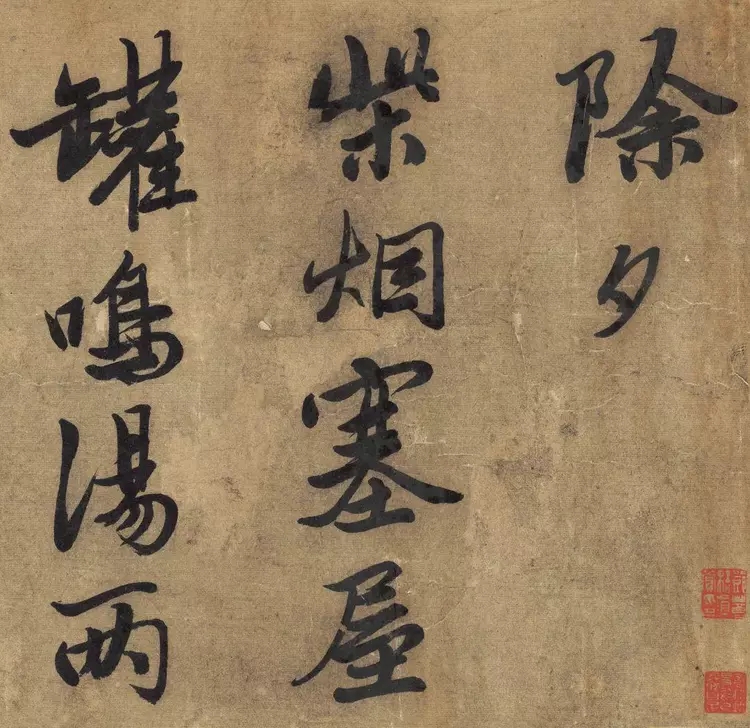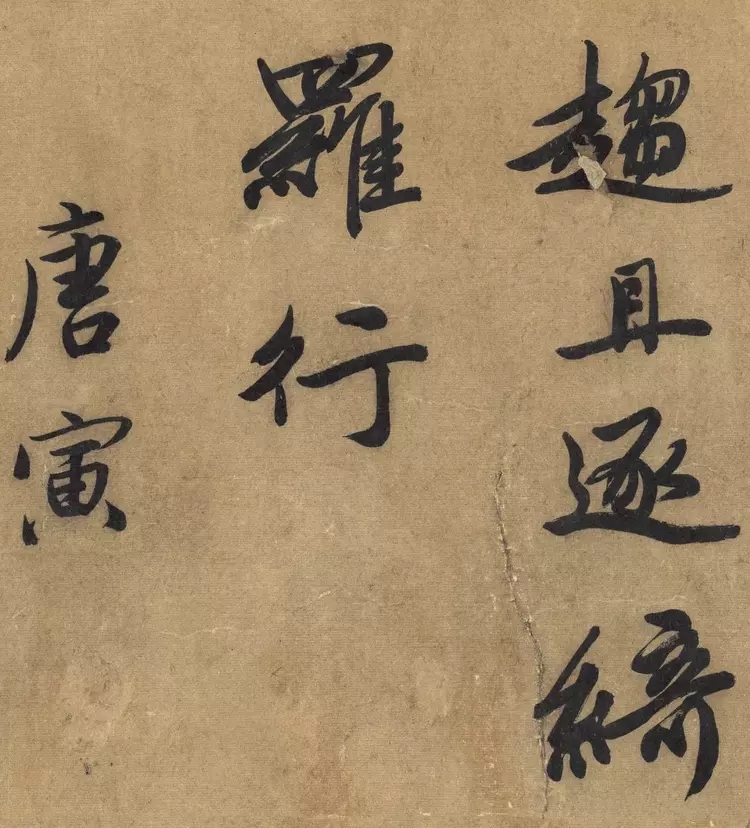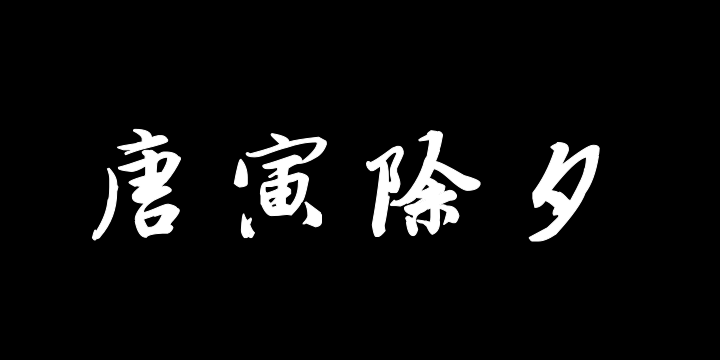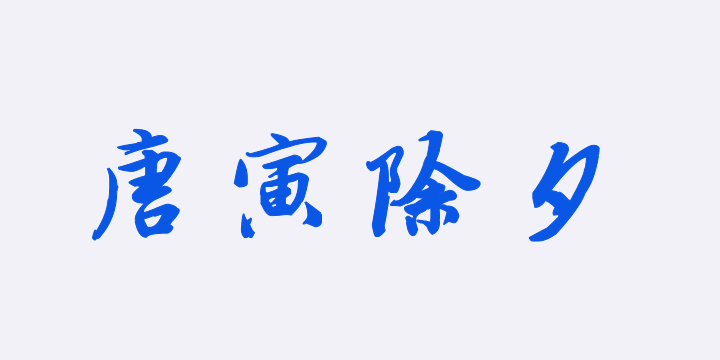
字体全名: 汉标唐寅除夕诗卷
字体简介: 下载须知:本字库非标准GB2312字库。本字库只包含了《唐寅除夕诗书》真迹上的“70个字”。详见图样。唐寅除夕诗书,引首29.5×60.5cm;书29.5×219cm。来源:株式会社东京中央拍卖2017春拍。题签:唐寅除夕诗书真迹。传研楼藏。引首:唐寅自书诗除夕卷真迹。钱君匋九十二岁。 唐寅是一位集诗、书、画“三绝”于一身的多才多艺的艺术家。唐寅的书法上溯晋唐,他早年书学怀仁集王羲之的《圣教序》,兼师李北海和欧阳询,深受元代赵孟頫影响。